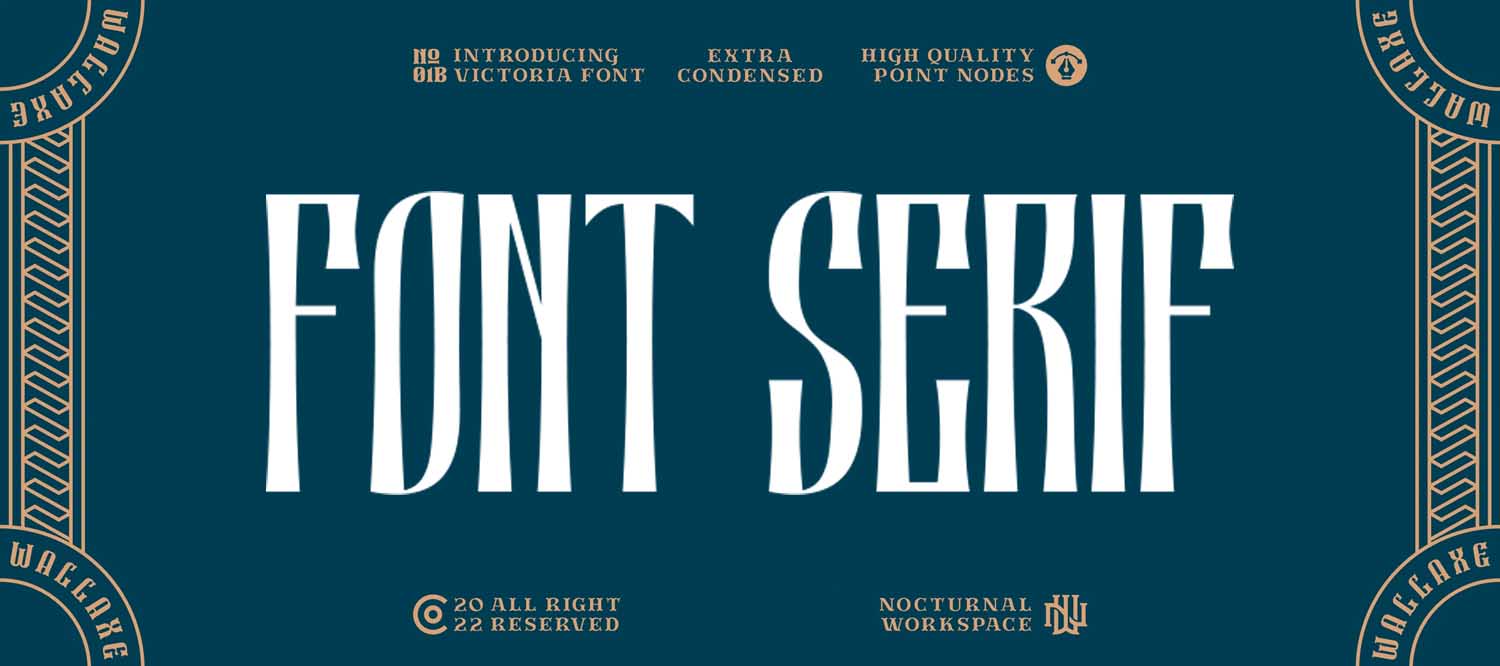
[Tải Xuống] Top 20 Font Serif (Chữ Có Chân) Việt Hóa Đẹp Nhất 2025
Trong thế giới thiết kế hiện đại, giữa muôn vàn font sans-serif tối giản, font chữ có chân (serif) vẫn giữ một vị thế không thể thay thế – với vẻ đẹp cổ điển, thanh lịch và đầy tính nghệ thuật. Từ sách in, poster, lookbook cho đến bộ nhận diện thương hiệu cao cấp, font serif luôn là lựa chọn lý tưởng cho những thiết kế mang tính truyền thống, sang trọng hoặc chuyên nghiệp.
Trong bài viết này, S99.vn sẽ giới thiệu đến bạn 20 font chữ có chân Việt hóa đẹp nhất 2025, được tuyển chọn kỹ lưỡng – hỗ trợ tiếng Việt đầy đủ, dễ sử dụng và phù hợp với mọi dự án thiết kế in ấn và kỹ thuật số.
Font chữ serif là gì?
Font chữ serif là kiểu chữ có nét gạch nhỏ (chân) ở đầu hoặc cuối các ký tự, tạo ra cảm giác:
• Cổ điển, trang trọng, lịch sự
• Dễ đọc khi in ấn văn bản dài
• Mang tính truyền thống, phù hợp thiết kế cao cấp
Vì sao font serif luôn được ưa chuộng?
• Tạo điểm nhấn thị giác tự nhiên
• Tăng tính thanh lịch và chuyên nghiệp
• Phù hợp với ngành hàng cao cấp, xuất bản, giáo dục
• Được tin dùng trong sách, tạp chí, hồ sơ thương hiệu
Top 20 Font Chữ Có Chân Việt Hóa Đẹp Nhất 2025
Dưới đây là danh sách các font serif Việt hóa đẹp, chuyên nghiệp và ứng dụng cao, được chọn lọc bởi đội ngũ tại S99.vn:
1. Font Máy Đánh Chữ Cổ Điển – TH HC Calvous Việt Hóa
Gợi lại hình ảnh thời bao cấp, TH-HC Calvous sở hữu kiểu dáng slab serif mạnh mẽ, chữ vuông vức, chắc nịch. Rất lý tưởng cho những thiết kế đòi hỏi sự vững chãi như poster cổ điển, biển hiệu, hoặc tiêu đề cần tạo điểm nhấn rõ ràng.
2. Font Chữ Có Chân Sang Trọng – TH Luxury 8 Cho Thương Hiệu Cao Cấp
TH Luxury 8 mang đến cảm giác chỉn chu và chuyên nghiệp nhờ các đường nét tròn đều, cân đối. Thiết kế mượt mà, khoảng cách hợp lý giữa các ký tự khiến font này đặc biệt phù hợp cho spa, thẩm mỹ viện, hoặc thương hiệu cao cấp.
3. Phông Chữ Bay Bổng Có Chân – TH Pinland Regular Cho Thiệp Cưới
Mềm mại và nhẹ nhàng, TH-Pinland Regular là lựa chọn tuyệt vời cho thiệp cưới, thư mời hay các thiết kế thiên về cảm xúc. Đường cong tinh tế, độ dày chữ vừa phải giúp truyền tải thông điệp một cách rõ ràng và duyên dáng.
4. Font Chữ Retro Có Chân – TH Juggernaut Phong Cách Vintage
TH Juggernaut tái hiện tinh thần retro cổ điển với chân chữ vuông vắn, chắc chắn. Lý tưởng cho poster tuyên truyền, biển quảng cáo vintage, hoặc các thiết kế mang đậm dấu ấn lịch sử, quân sự.
5. Font Serif Công Nghệ – TH Degrad Mono Gọn Gàng, Kỹ Thuật
Với thiết kế đồng đều, sắc nét và gọn gàng, TH-Degrad Mono thể hiện phong cách công nghệ rõ rệt. Font này phù hợp cho UI/UX, thiết kế web, hoặc các ấn phẩm đòi hỏi sự tối giản và chính xác kỹ thuật.
6. Font Máy Đánh Chữ Cứng Cáp – TH Cungcap 12 Việt Hóa
Nếu bạn đang tìm một font dễ đọc ở khoảng cách xa và thể hiện được sự mạnh mẽ, TH Cungcap 12 là lựa chọn đáng giá. Đường nét to, chắc và vuông vức giúp font phát huy tối đa trên biển hiệu, poster công trình hoặc thiết kế quảng cáo cần độ rõ cao.
7. Font Chữ Có Chân Mềm Mại – TH Luxury 7 Dành Cho Spa, Mỹ Phẩm
Mang hơi hướng thẩm mỹ và làm đẹp, TH Luxury 7 kết hợp giữa sự mềm mại và sự tinh tế. Với các chi tiết nhẹ nhàng, font này phù hợp cho logo spa, tiêu đề web thời trang hay ấn phẩm marketing cao cấp.
8. Phông Chữ Tinh Tế Có Chân – TH Luxury 6 Dễ Ứng Dụng
TH Luxury 6 có thiết kế giao thoa giữa hiện đại và cổ điển, đường nét sắc sảo, chân chữ vững vàng. Font dễ dàng ứng dụng trong thiết kế nhận diện thương hiệu, tạp chí hoặc các dự án đòi hỏi sự chuyên nghiệp.
9. Font Chữ Serif Thời Trang – TH New York Cao Cấp, Hiện Đại
TH-Newyork mang đến phong cách cao cấp, hiện đại. Chữ thanh mảnh, cao ráo với bố cục hài hòa – rất hợp để dùng trong lĩnh vực thời trang, tạp chí hoặc các thương hiệu theo đuổi phong cách tối giản.
10. Font Chữ Nghệ Thuật Cổ Điển – TH Red Rose Việt Hóa
Với 4 kiểu chữ mang hơi hướng cổ điển, TH-Red Rose là bộ font lý tưởng cho các thiết kế mang tính nghệ thuật như bìa sách, poster phim, thiệp cưới. Font kết hợp giữa sự mềm mại và đường nét sắc sảo, đầy cuốn hút.